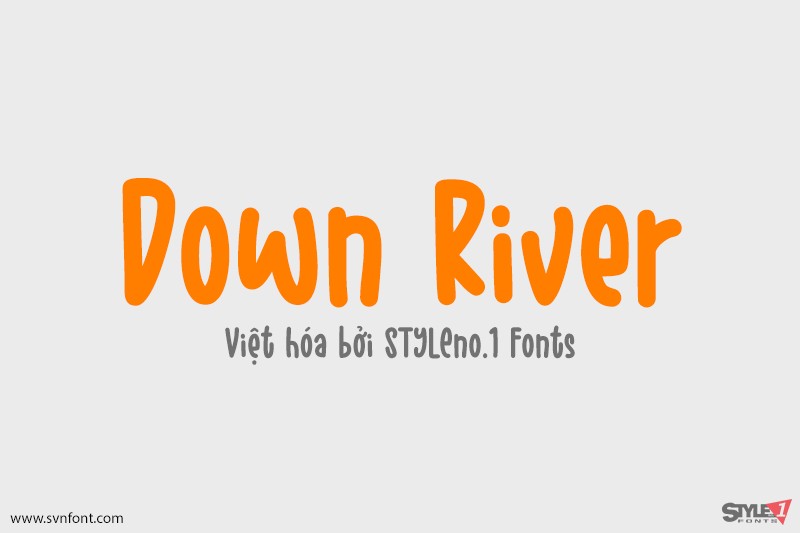
Tải Ngay Font Việt hóa SVN Down River – Đẳng Cấp Thiết Kế Ấn Tượng
Trong thế giới đồ họa hiện đại, việc lựa chọn bộ Font Miễn Phí chất lượng là yếu tố then chốt tạo nên sự khác biệt cho các dự án sáng tạo. Font Việt hóa SVN Down River nổi lên như một giải pháp hoàn hảo cho những ai đang tìm kiếm sự mạnh mẽ và độc đáo. Đây là bộ phông chữ thuộc phong cách sans-serif hiện đại, được đội ngũ SVN tinh chỉnh tỉ mỉ từng dấu câu để tương thích hoàn toàn với bảng mã Unicode tiếng Việt, giúp người dùng không còn lo lắng về lỗi hiển thị khi soạn thảo văn bản hoặc thiết kế ấn phẩm.
Khám phá sức hút của Font Việt hóa SVN Down River trong thiết kế
Bộ phông này gây ấn tượng mạnh nhờ cấu trúc chữ vững chãi, đường nét dứt khoát nhưng vẫn giữ được sự tinh tế cần thiết. Nó mang lại cảm giác chuyên nghiệp, phù hợp cho cả mục đích học tập lẫn công việc chuyên môn.
Tính ứng dụng linh hoạt của bộ chữ
Với độ dày nét vừa phải và khoảng cách các chữ được căn chỉnh khoa học, Font Việt hóa SVN Down River cực kỳ hữu dụng trong việc thiết kế tiêu đề sách, bìa tạp chí, banner quảng cáo hay các bài thuyết trình tại trường học. Khả năng hiển thị rõ nét trên cả màn hình kỹ thuật số và bản in giúp học sinh, sinh viên dễ dàng trình bày ý tưởng một cách lôi cuốn nhất.